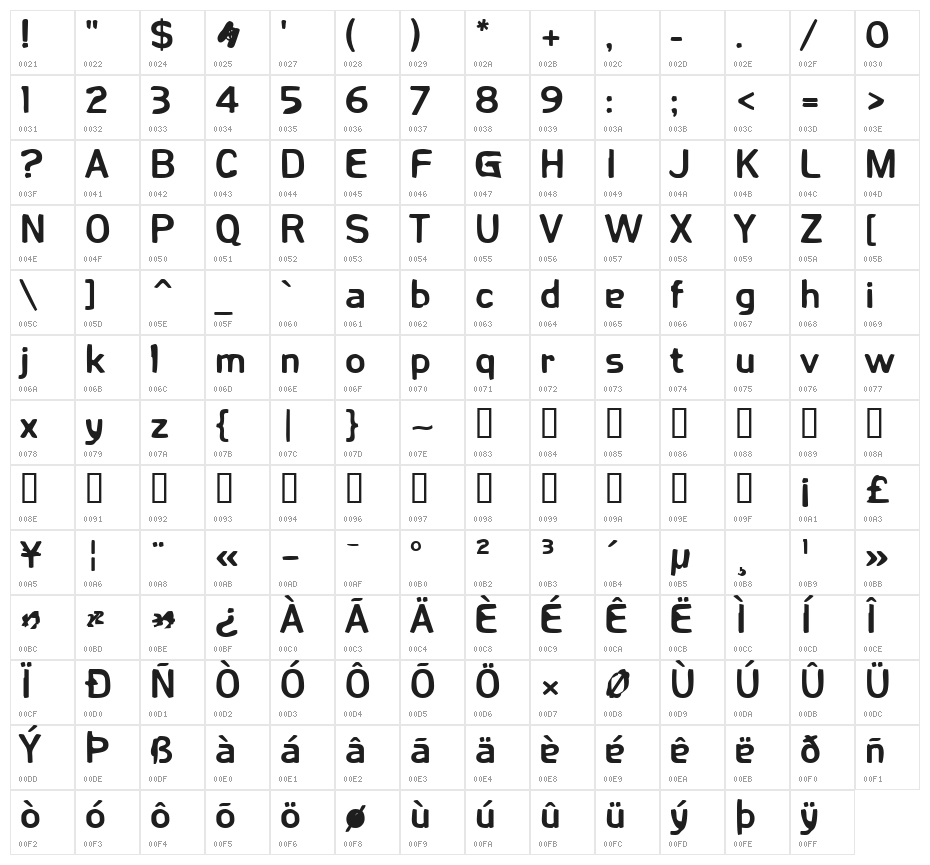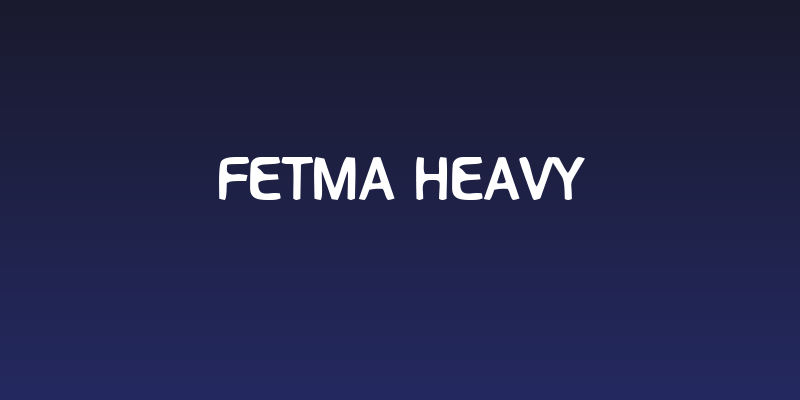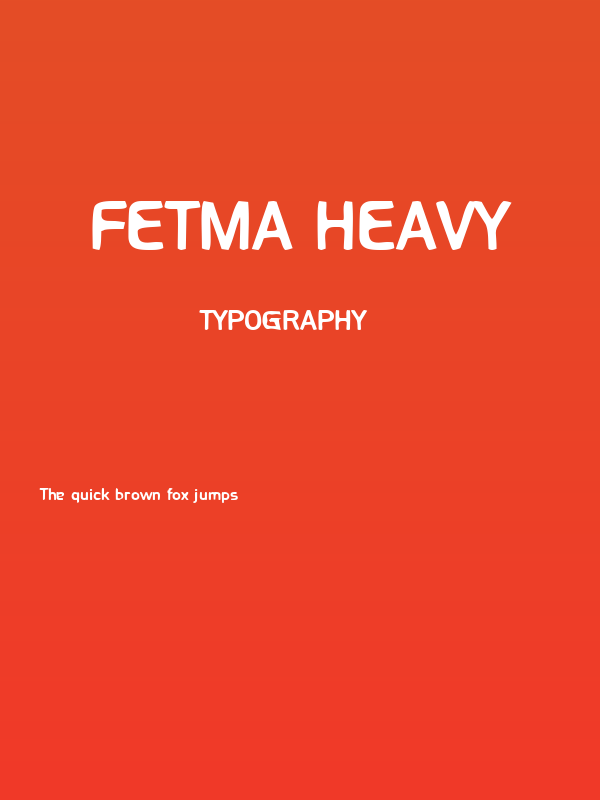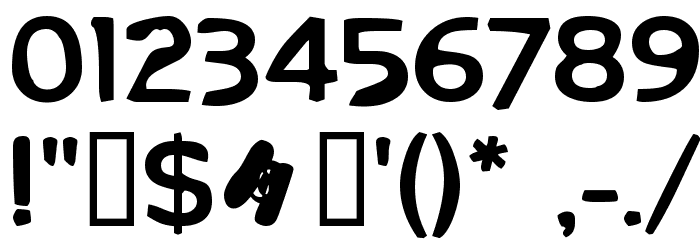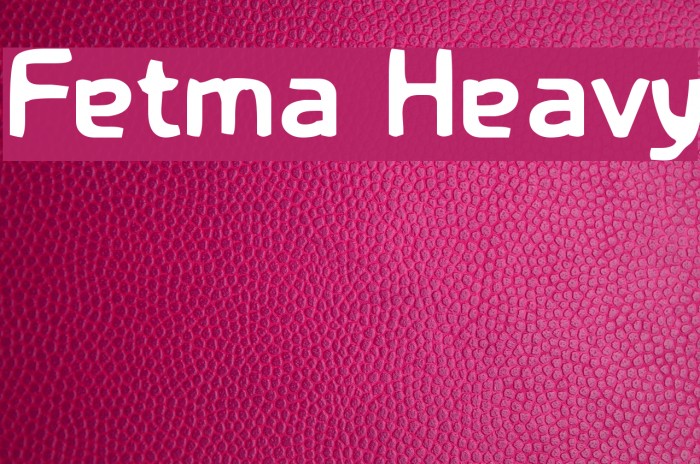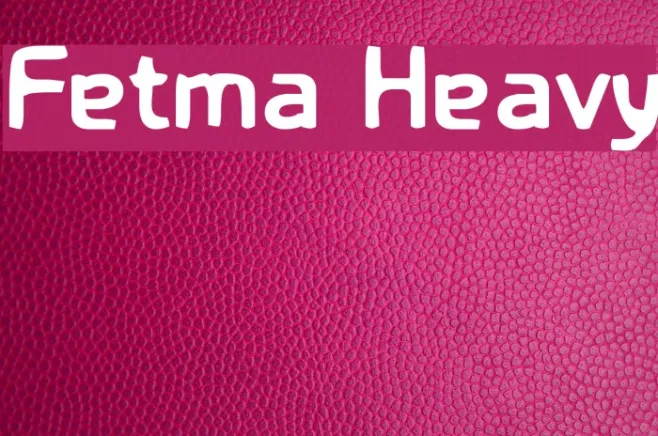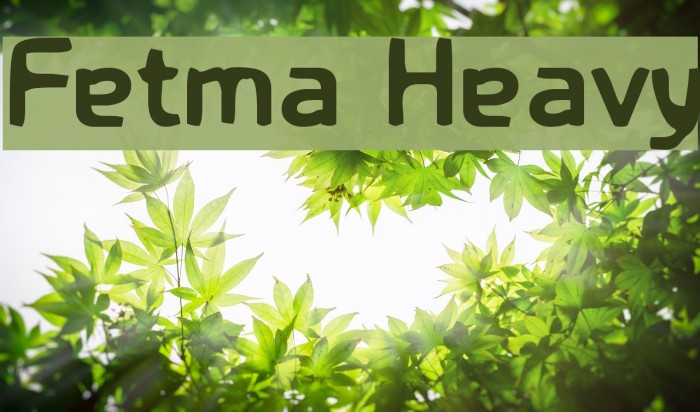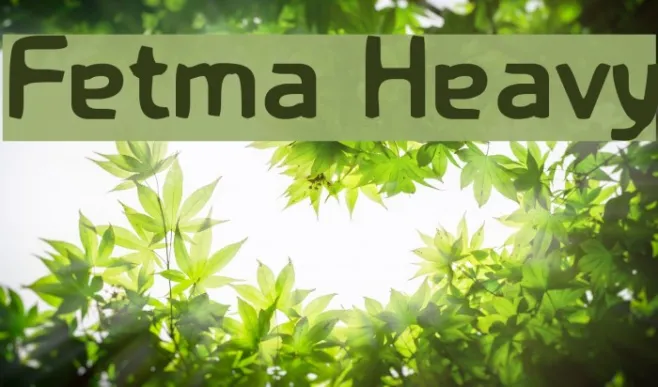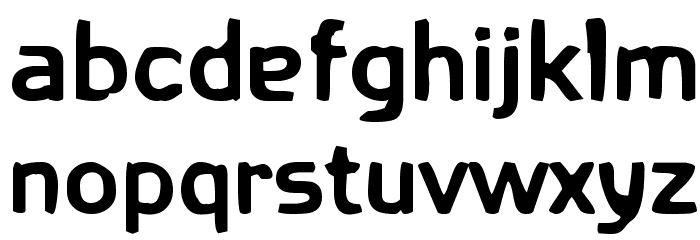
Fetma Heavy Font
| Stile generale | Playful, Modern |
| Progetti proposti | Ideal for children's books, playful branding, posters, and headlines that need a strong visual impact. |